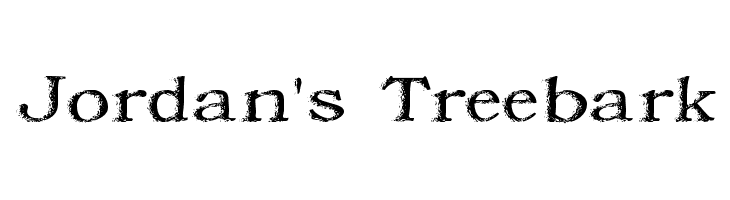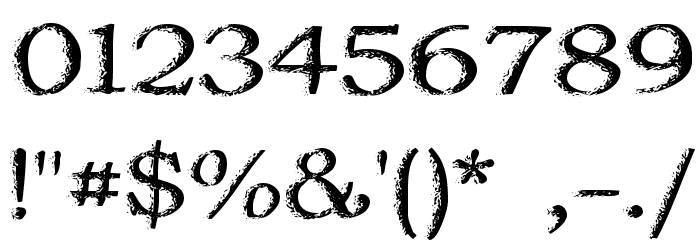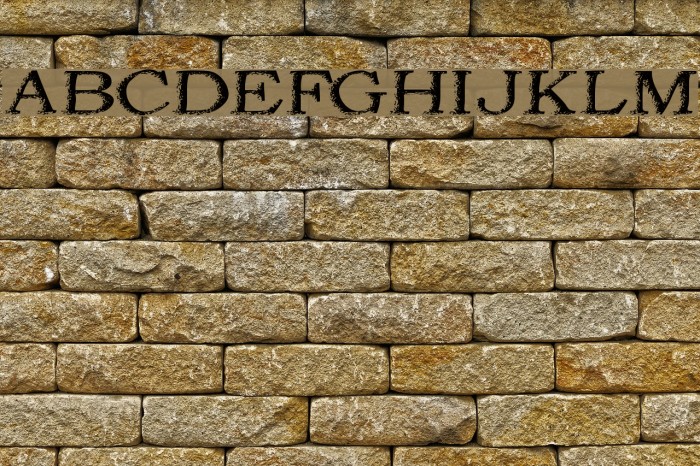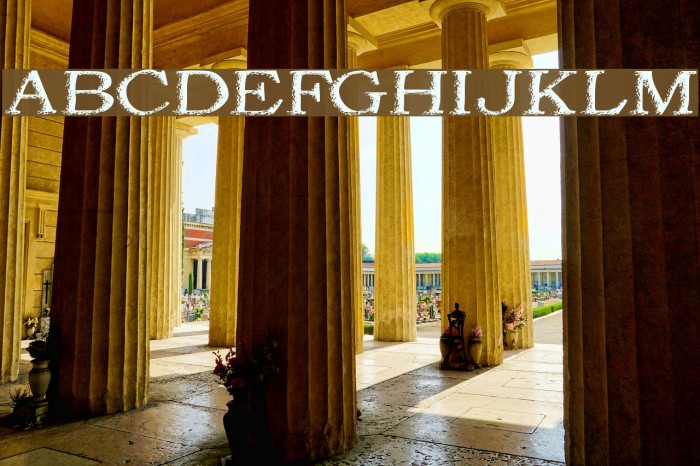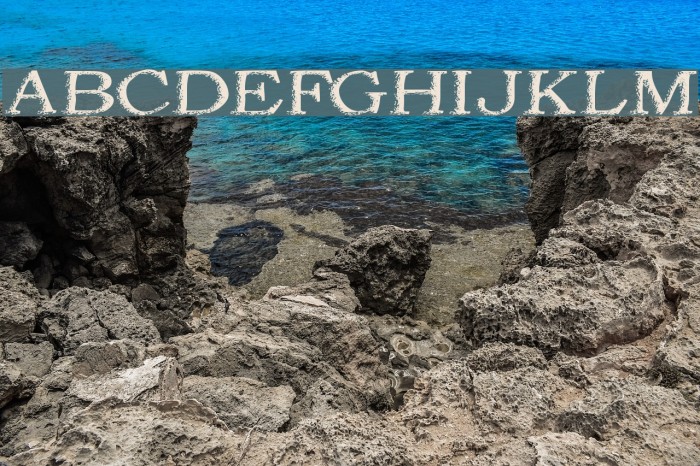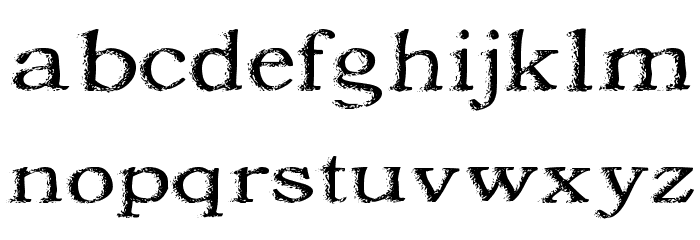
Jordan's Treebark Font
| Projets proposés | Ideal for nature-themed designs, outdoor event posters, eco-friendly brand logos, and rustic wedding invitations. |